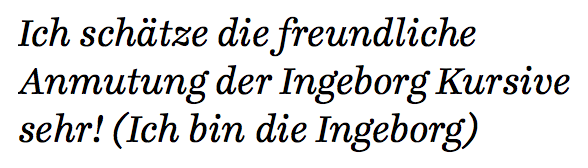
Suche eine Schrift, die eine ähnliche Kursive hat wie die Ingeborg
Hallo Leute, ich bin auf der Suche nach einer dynamischen Antiqua die eine Kursive hat, die ähnlich zur Ingeborg ist.
Die Kursiven die man der Scotch-Roman zuordnen kann fände ich sehr interessant für mein Projekt. Allerdings passt der Regular-Schnitt der Scotch-Roman-ähnlichen-Schriften nicht zu meinem Projekt (zu statisch).
Der Kursiv-Schnitt sollte sich nicht zu sehr ins Schriftbild integrieren.
Ich habe schon überlegt eine Regular mit dynamischen Charakter mit einer Kursiven einer Clarendon-Artigen zu kombinieren, aber ich will mir auch nicht zuviel zumuten.
Ich bin also auf der Suche nach einer dynamischen Antiqua mit einer peppigen Kursiven (Regular-Schnitte die mag: Guardian, Tisa)
Hmm … schwierig – eine humanistische Aufrechte kombiniert mit einer klassizistischen Kursiven. Ich frage daher erstmal noch paar statische Gesamtpakete ab und nähere mich nach unten zu Hybrid-Ansätzen.
Also – schon diese angesehen?:
• Eames
• Miller
• Benton Modern
• Century Schoolbock
• Mrs Eaves
• New Caledonia
• FF Quixo
• FF Franziska
• Rabenau
• FF Celeste
Oder auch alle noch zu statisch?
Wie wäre es mit der Rabenau von Bertram/Frohloff?
Die Schrift muss auch für eine Wortmarke funktionieren, aber viele der vorgestellten Schriften erregen im Detail viel zu viel Aufmerksamkeit.
Die Bullen finde ich super, aber die ist schlecht ausgebaut.
Die Turnip mit augeprägteren Ober- und Unterweiten und einer auffallenderen Kursive, das wäre wohl meine Wahl.